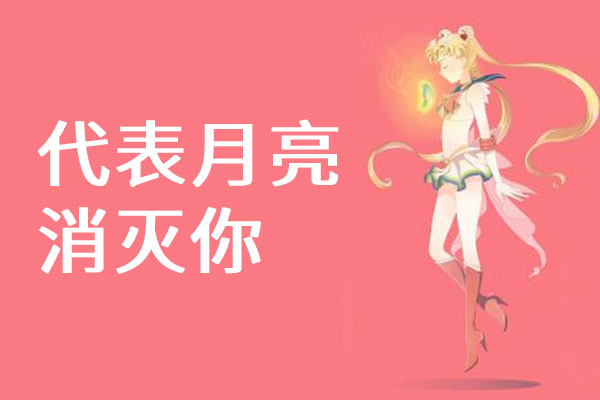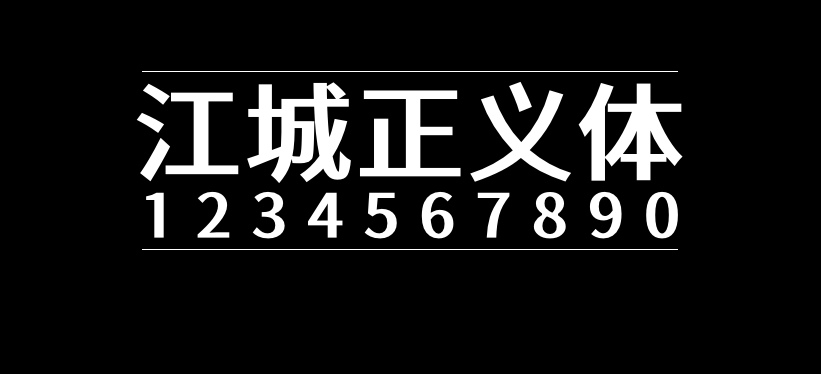
字体下载 江城正义体
江城正义体
江城正义体(jiangchengzhengyiti)是国内字体爱好者刘鹏基于思源黑体改造的一款字体,把思源黑体的笔画在横向上调细处理,纵向增粗处理。这款字体削减了横笔的粗细,使字体看上去更具现代感。比较适合用于海报标题,LOGO等方面的设计,用来进行二次字体设计创作也会方便很多!
这款江城正义体是基于中国版思源黑体改造,符合中国大陆的习惯,字符比较全,简体和繁体基本都不缺字,而且包含有5个字重。